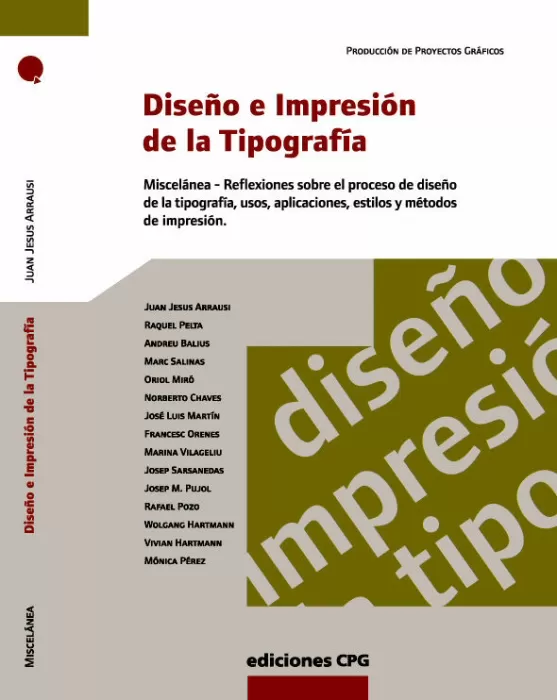
DISEÑO E IMPRESIÓN DE LA TIPOGRAFÍA
MISCELÁNEA CON TEXTOS DE DOCE AUTORES
DISEÑO E IMPRESIÓN DE LA TIPOGRAFÍA
Es una miscelánea que recopila una serie de reflexiones sobre el proceso de diseño de la tipografía, usos, aplicaciones, estilos y los métodos de impresión, realizadas por una selección de autores de reconocido prestigio y profesores universitarios en las diversas especialidades del diseño.
Autores:Andreu Balius, Oriol Miró, Juan Jesús Arrausi, Marc Salinas, Raquel Pelta, Marina Vilageliu, Josep Sarsanedas, Norberto Chaves, José Luis Martín, Félix Bella, Xavier Llopis, Francesc Orenes, Rafael Pozo
Josep M. Pujol, Wolgang Hartmann, Vivian Hartmann.